Mais de 20 fontes de caligrafia gratuitas para designers
Publicados: 2018-07-17A tipografia é uma parte muito importante de qualquer design, como sites, folhetos, banners, logotipos e muito mais. É extremamente importante que todos os elementos de design, incluindo o tipo e o tamanho da fonte, estejam em coordenação com o design. A fonte certa pode fazer ou quebrar um design, se a fonte não for legível, o resto do design não faria sentido para os leitores. As fontes de caligrafia gratuitas também são muito importantes para sites, pois tornam o conteúdo mais atraente e legível. Então, quando os designers estão criando um site ou banner, eles precisam ir além das fontes usuais e buscar fontes caligráficas.
A caligrafia é uma técnica de criação de letras artísticas, evoluiu e agora temos fontes de caligrafia gratuitas que estão em algum lugar entre escrever e desenhar. Estes dão muita profundidade e singularidade a um projeto. Felizmente, existem muitas fontes caligráficas disponíveis na web. Mas, é uma tarefa pesquisar o tipo certo de fontes de caligrafia gratuitas nessas centenas de opções e pode matar muito tempo precioso dos designers. Eu vasculhei uma variedade de fontes e reuni uma lista de mais de 20 fontes de caligrafia gratuitas para designers.
Se você deseja melhorar a apresentação do seu produto e impressionar os clientes, basta usar as fontes de caligrafia gratuitas certas. No entanto, é difícil obter uma fonte com classe, especialmente quando você não quer pagar por serviços de um calígrafo profissional.
Essas fontes não podem ser comparadas com fontes comuns. Essas fontes de caligrafia gratuitas usam um estilo de script que emula a aparência da caligrafia. Nós fornecemos para você uma enorme coleção de estilos de caligrafia que você pode selecionar.
Tipos de fontes de caligrafia gratuitas
Existem 3 tipos existentes de fontes de caligrafia, incluindo árabe, oriental e ocidental. Cada tipo mostra a caligrafia e o idioma de diferentes regiões do mundo. A caligrafia inglesa é refletida pela caligrafia ocidental, enquanto a caligrafia oriental demonstra alfabetos asiáticos. A caligrafia árabe é completamente baseada no alfabeto árabe.
Neste post, forneceremos todas as fontes de caligrafia premium que você pode encontrar online. Mas, falaremos mais sobre caligrafia ocidental. As fontes de caligrafia ocidentais são atraentes e profissionais. A melhor coisa sobre eles é que eles são gratuitos. Portanto, você deve baixá-los, passar por cada um antes de escolher o que deseja.
O pincel de Alex é uma fonte clássica que é muito clara e elegível. Tem um espaçamento muito decente entre as letras, isso significa que essa fonte pode ser usada em parágrafos densos de conteúdo.
1) Madalena
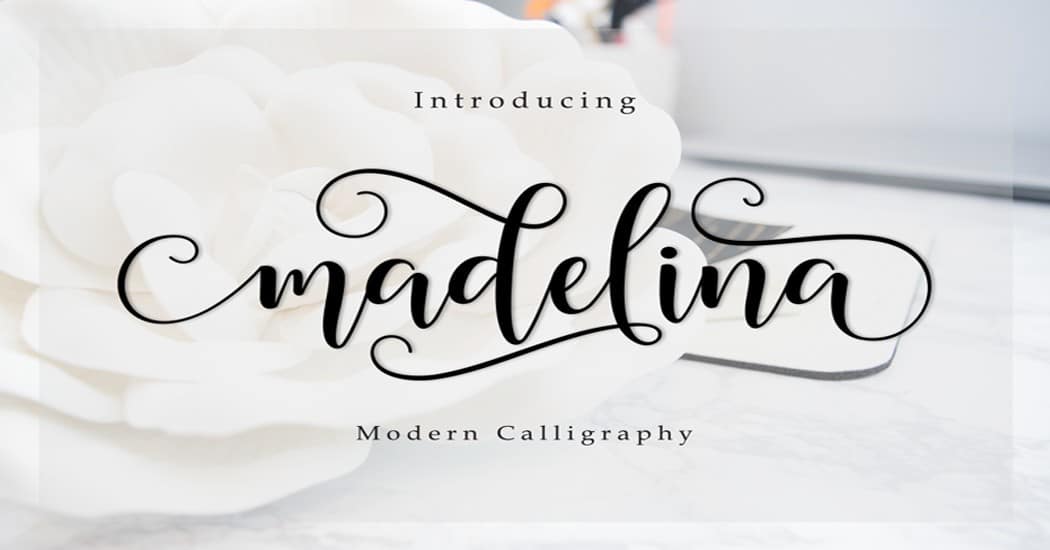
A fonte Madelina provavelmente impressionará você com seu belo estilo de caligrafia artesanal. É uma boa ideia usar caracteres decorativos desse tipo para escrever convites em cartões de visita e cartões de felicitações. A fonte também fica bem em materiais de marca.
2) O colapso
O Breakdown obviamente faz a diferença como a fonte com um design bonito e elegante. Se você optar por obter a versão comercial completa dessa fonte, receberá um conjunto de glifos alternativos, bem como ligaduras contextuais. Assim, você poderá criar seu próprio estilo.
3) Natasa
Natasa é o novo tipo de fonte de arte. A fonte tem o design de estilo moderno. A fonte permite que os artesãos projetem o que quiserem.
4) Traga o coração
Bring Heart é a fonte de caligrafia de estilo moderno com um estilo de design bonito e elegante. Não há dúvida de que os artesãos acharão fácil integrar essa fonte com designs de diferentes tipos.
5) Campainha
Bluebell é a fonte de caligrafia de estilo moderno que tem uma aparência bonita e natural. Essa fonte pode ser usada para projetos de diferentes tipos, incluindo anúncios, designs de etiquetas, designs de casamento, logotipos e branding, design de produtos e embalagens.
6) Austin
Os artesãos certamente acharão fácil criar cartões de visita, cartões comemorativos, materiais de marca e outros tipos de projetos com a fonte Austina especialmente codificada. É muito fácil obter acesso aos recursos Open Type com programas como Adobe Photoshop, Adobe Illustrator e muitos outros.
7) Terras Irmãos
A fonte Brother Lands tem um estilo de pincel sólido e um charme pessoal. Esta bela fonte é uma boa opção para projetos como design de camisetas, design de moda, projetos de branding, design de revistas e outros.
8) Notas de Hijr
Hijrnotes é uma fonte muito incomum. Hijrnotes tem maiúsculas grandes e minúsculas pequenas. Acima de tudo, a fonte é elegante e fácil de ler. Você pode usar essa fonte para criar cartões de visita, letreiros de néon, panfletos e pôsteres de tipografia de citações.
20) Caligrafia de inverno
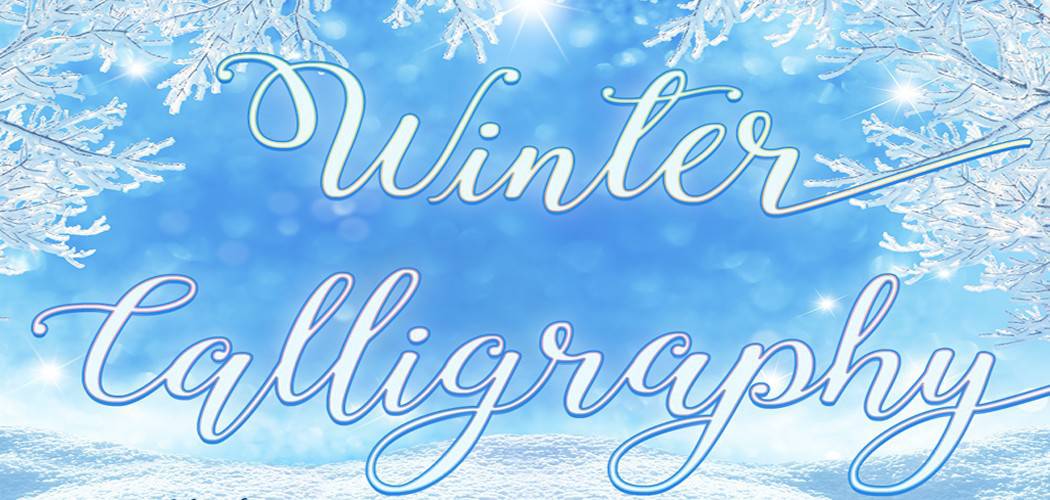
Gostaria de adicionar um toque pessoal ao seu projeto? Nesse caso, você definitivamente deve aproveitar a fonte Winter Calligraphy. Esta nova e impressionante fonte de arte manuscrita tem centenas de alternativas. Você definitivamente achará fácil usar essa fonte para qualquer tipo de projeto.